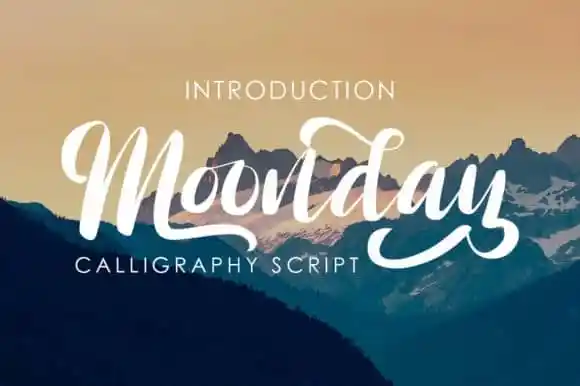
Monday Script Font – Download Grátis
A Monday Script Font é uma elegante e fluente fonte escrita a mão, ideal para quem busca um estilo natural e único. Essa fonte foi criada pelo designer Green Adventure Studio e traz linhas suaves e alternativas incríveis que realçam seus traços de forma surpreendente. Com seu desenho fluido e estilo natural, essa fonte é perfeita para várias aplicações gráficas. Seu design amigável e sua disposição única fazem dela uma escolha excelente para projetos em diversos campos. O potencial dessa fonte é infinito, apenas a imaginação lhe dá limites. Se você está procurando por uma fonte escrita a mão que seja tanto uma graça quanto uma ótima opção de design, então a Monday Script Font certamente faz parte da sua seleção.